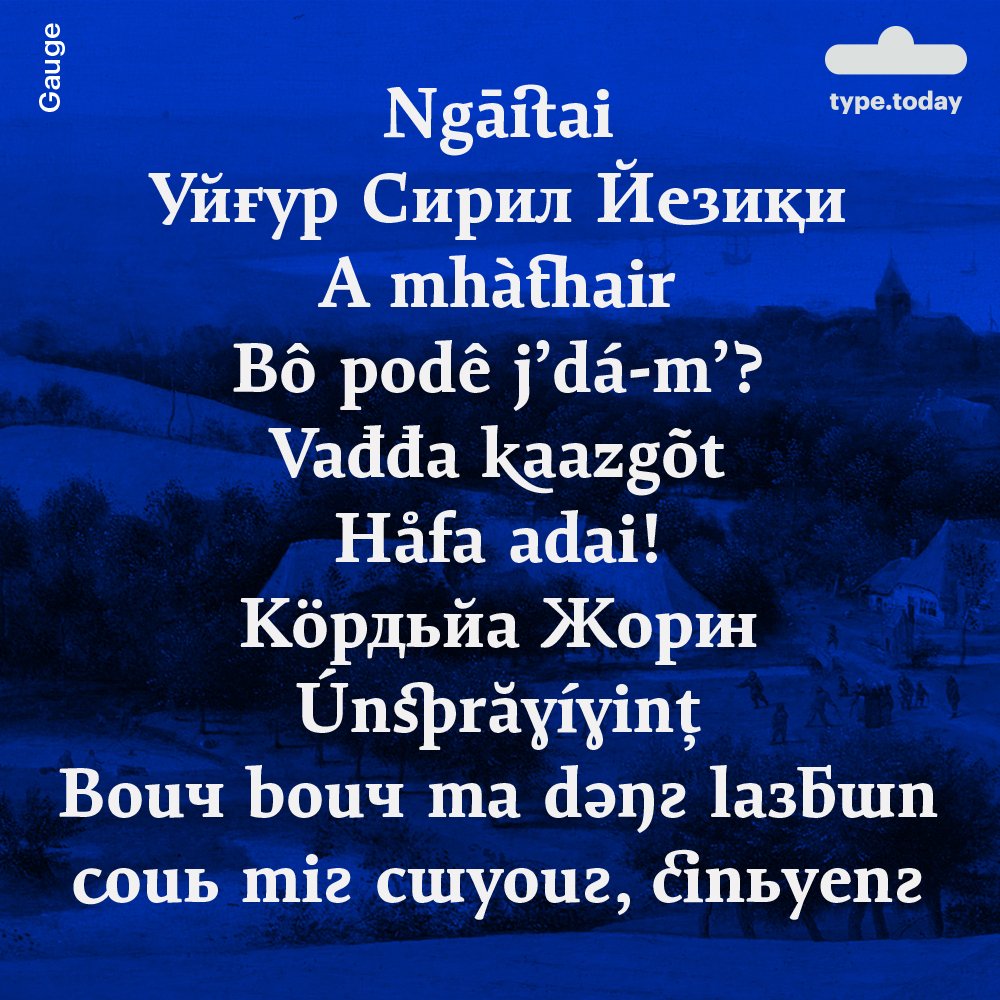
У Gauge Caption, Text, Head и Display есть версия Pro. В ней около шестисот лигатур, дополнительные наборы цифр, дроби, знаки с росчерками и наборные украшения. Эта версия поддерживает более двухсот языков на основе кириллической и латинской письменностей, включая, например, абхазский, бамана, вьетнамский, кильдинский, саамский и фула.
Gauge Caption, Text, Head и Display
Интерполяция Gauge
Gauge Letterpress
Обложки журнала «Афиша» с первой версией Gauge